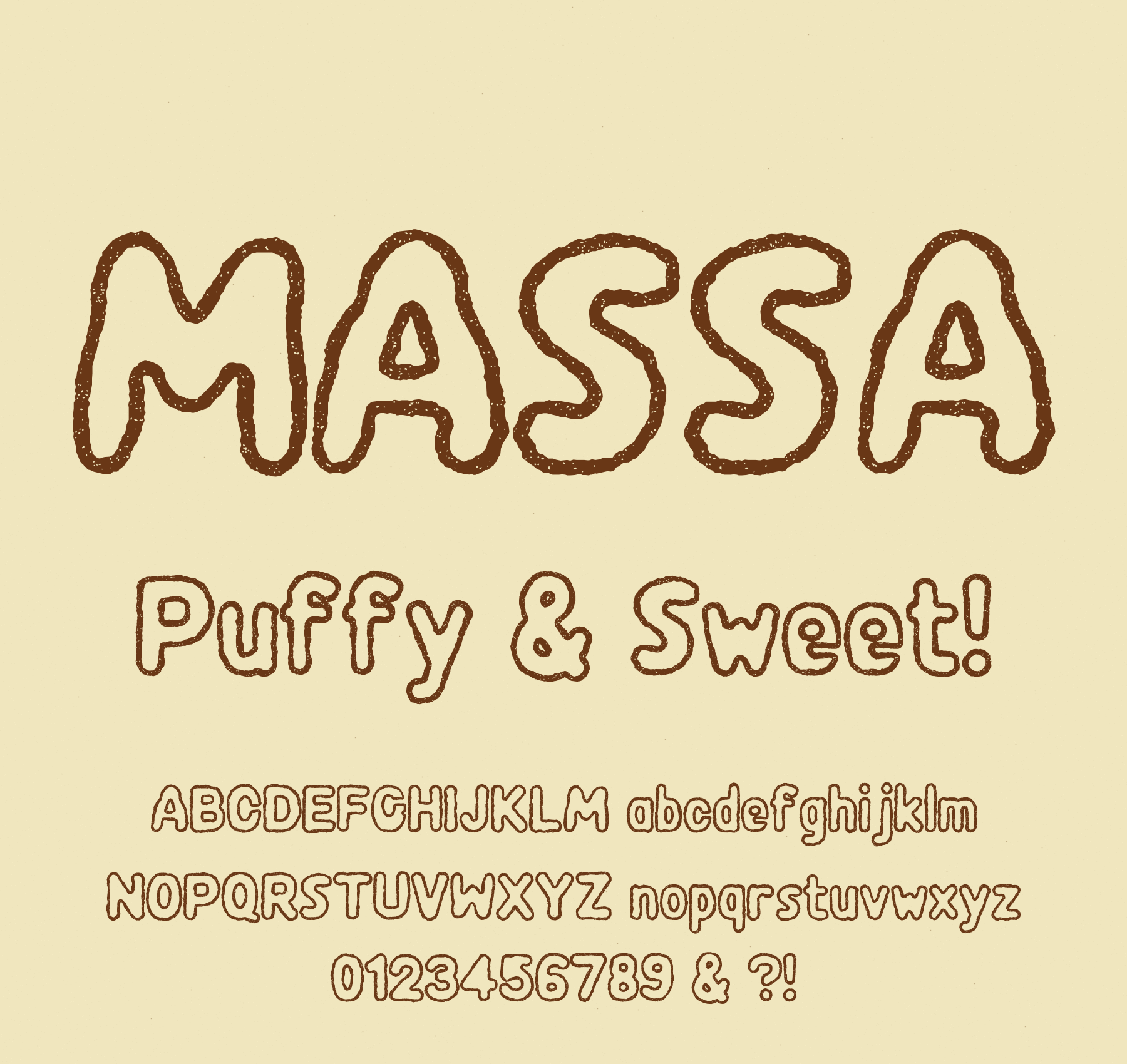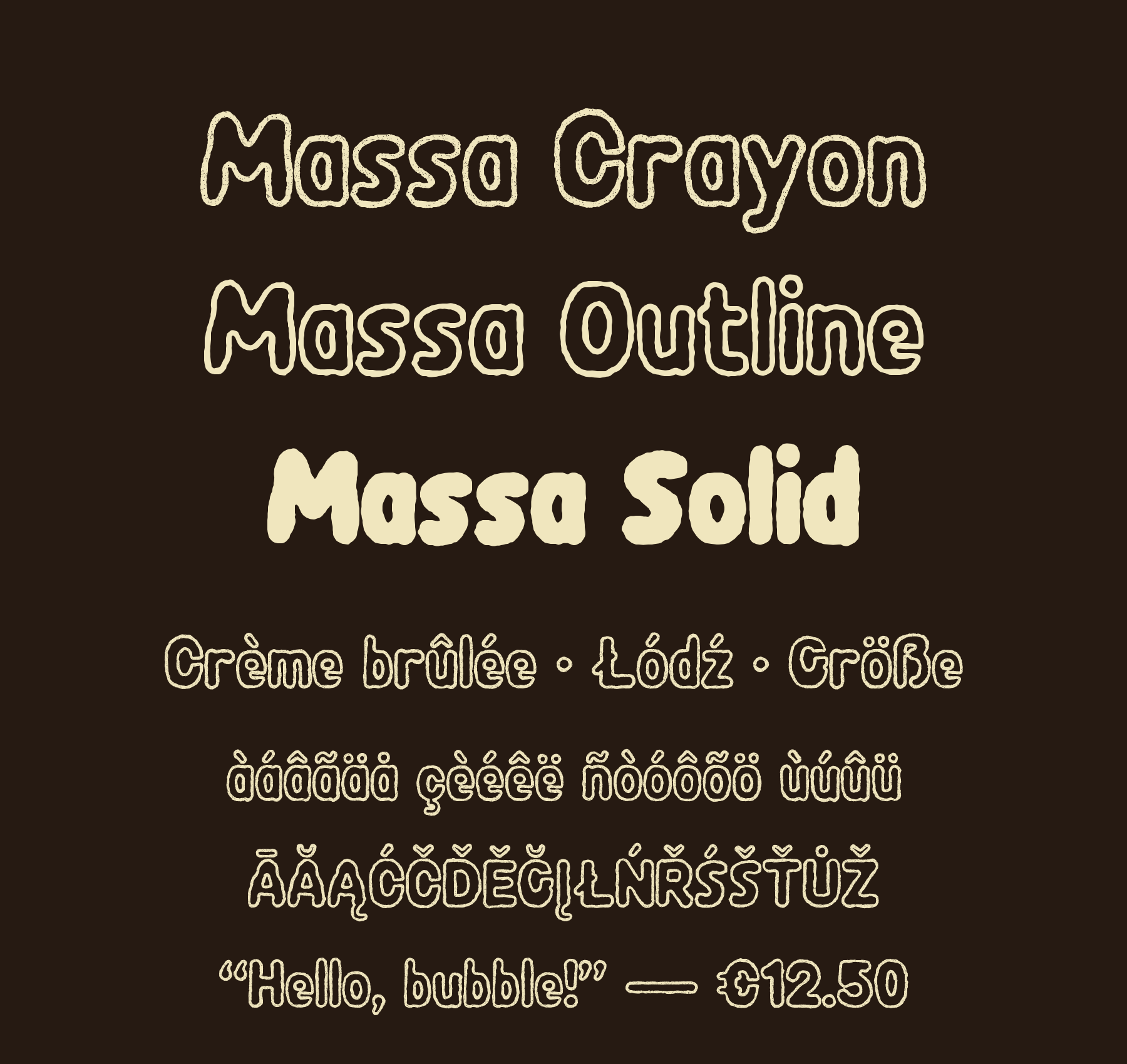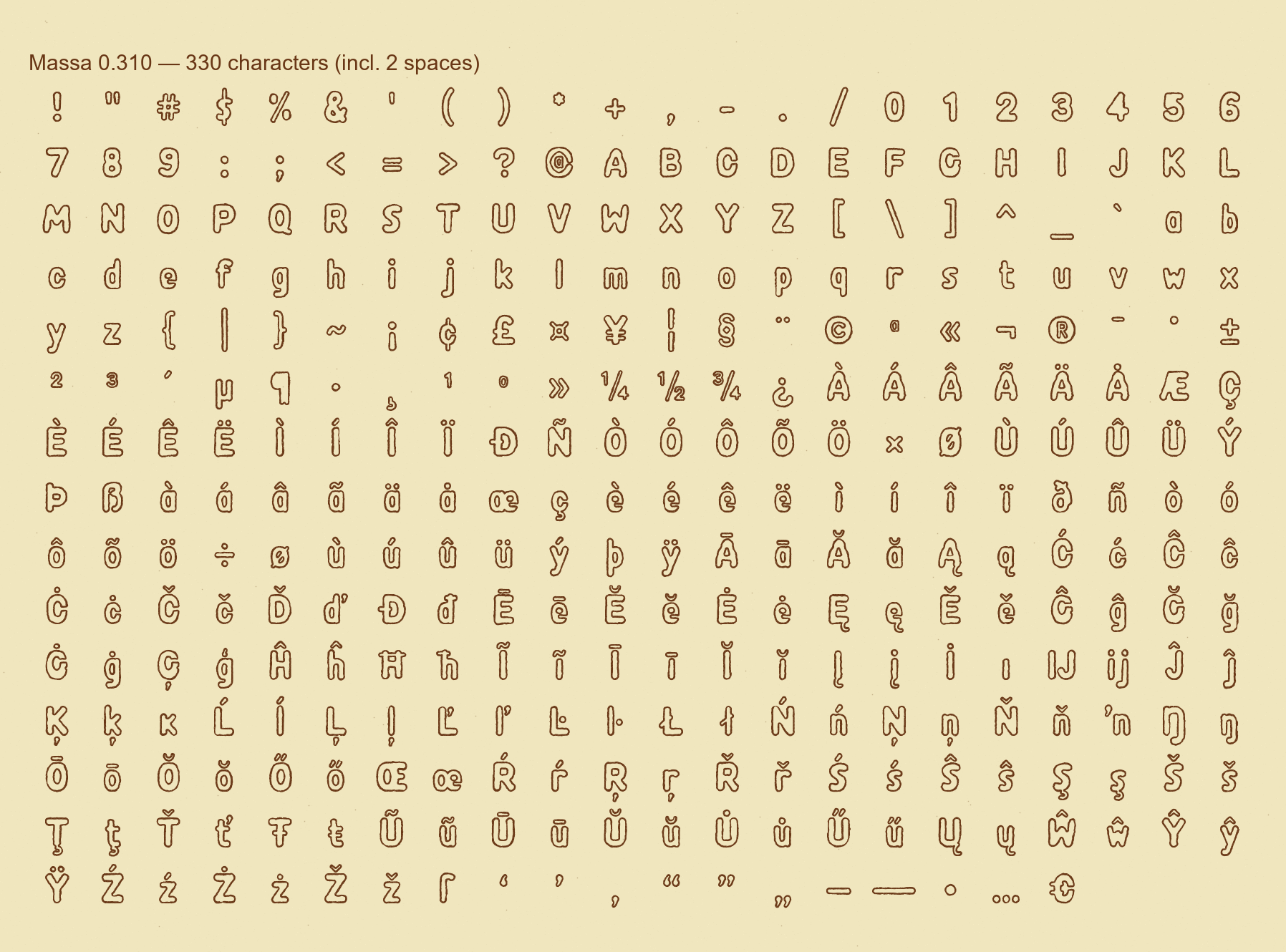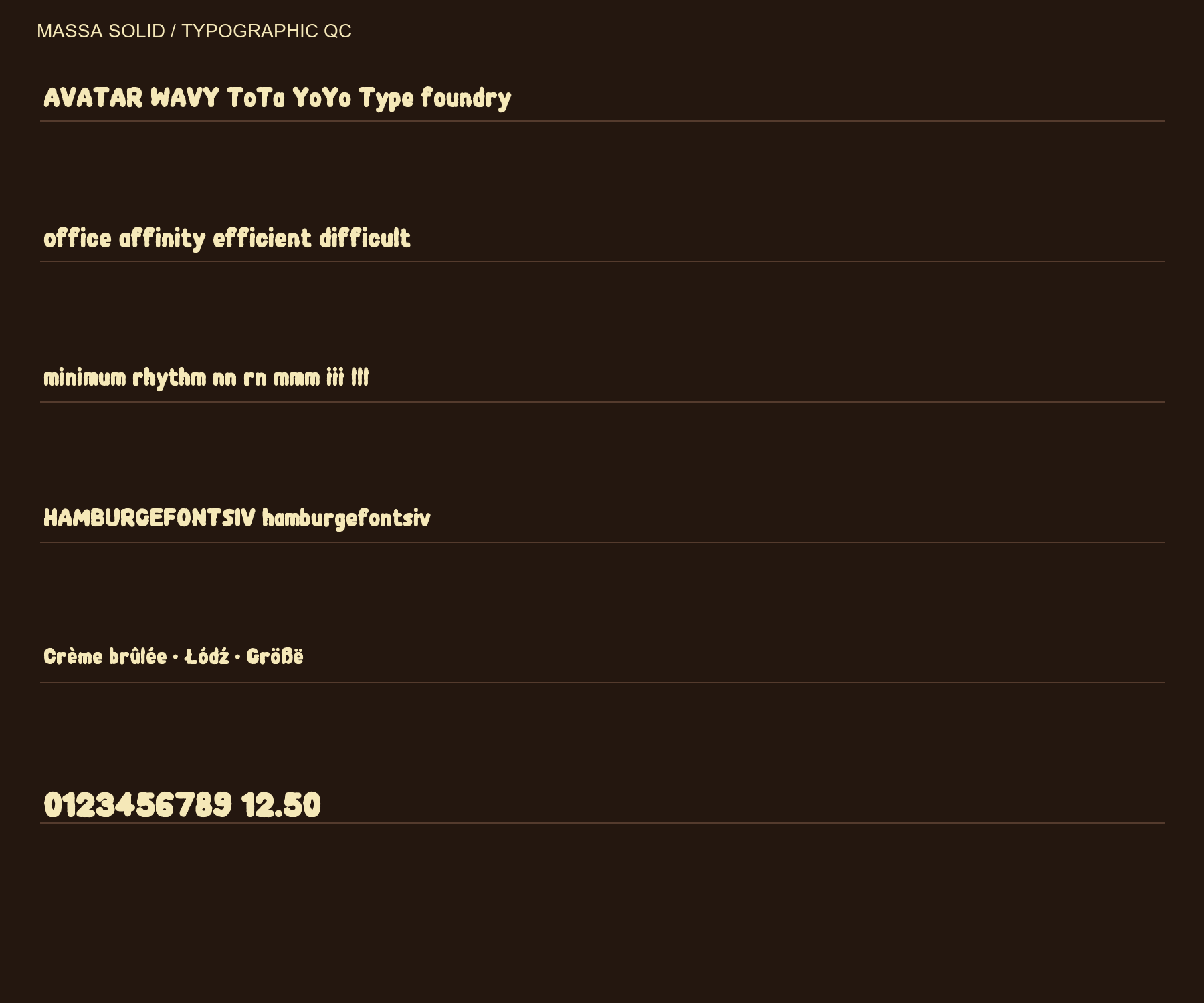
Massa는 둥글고 손으로 그린 듯한 외곽, 말랑한 연결부, 풍선 같은 내부 공간을 가진 카툰 디스플레이 폰트입니다. Crayon·Outline·Solid 세 스타일을 함께 제공합니다. 버전 0.320. 영문 대소문자·숫자·기호·악센트·확장 라틴 330자. 이번 업데이트에서 세 스타일에 공통 주요 조합 커닝을 추가했습니다. TTF·WOFF2와 세 스타일 통합 ZIP을 제공합니다. 큰 제목·포스터·패키지 그래픽용입니다. 작은 본문에서는 Outline 내부 공간과 Crayon 질감이 약해질 수 있습니다. 한글은 포함하지 않습니다. SIL OFL 1.1 무료 공개.
331 glyphs. Use the character grid and type tester to check the exact characters needed for your project.